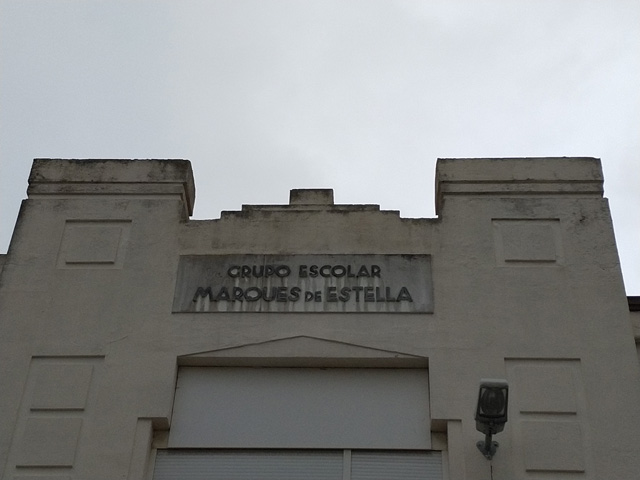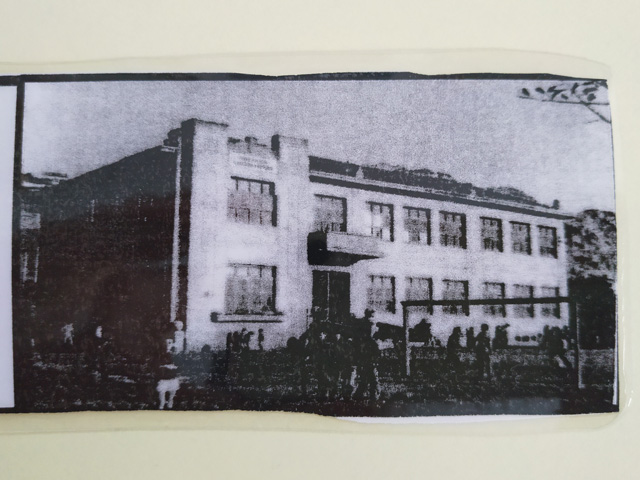
Grupo Escolar Marques de Estella (1929)
El próximo 31 de agosto el CEIP Marqués de Estella cumplirá 90 años de servicio. Las antiguas escuelas de Peñacastillo, con un diseño marcado de caracter regionalista para lo que fue la época, fueron proyectadas en 1927 por el Arquitecto Municipal Ramiro Saiz Martínez, que sustituyó a González – Riancho. Este mismo arquitecto también diseñó los Jardines de Piquío.
El colegio fue inaugurado el 31 de agosto de 1929 por los Reyes Alfonso XIII y Victoria Eugenia, así como por el propio Marqués de Estella que era Primo de Rivera. En una de sus paredes, encima de la antigua entrada principal, aún se puede ver el rótulo original de la época dentro de un placa en piedra, donde se puede leer: «GRUPO ESCOLAR MARQUES DE ESTELLA».
Llama la atención la limpieza de la tipografía, de palo seco, característica de esa época. Pero si os fijáis bien tiene unos detalles curiosos: La «G» es minimalista; La «Q» está invetida y las dos «S» de la segunda linea un poco inclinadas.
Pocos colegios de la ciudad guardan estos pequeños tesoros tipográficos originales de la época.
Foto de época donde se puede ver el edificio primigenio y la placa con el rótulo. Fuente desconocida.